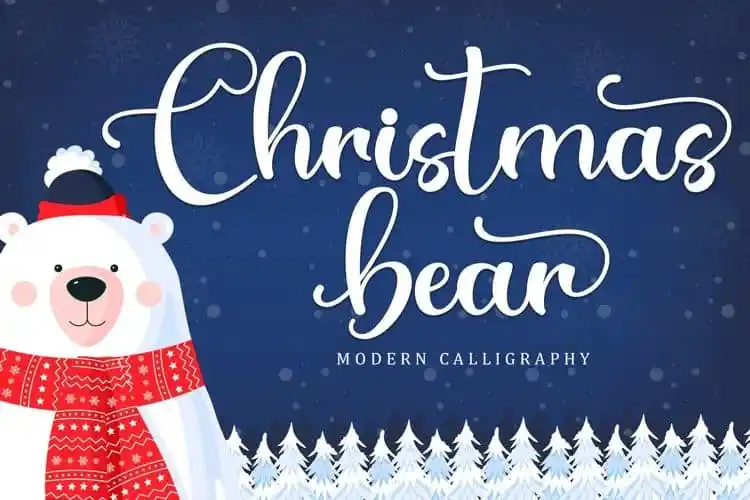
Christmas Bear Calligraphy Font é uma bela tipografia moderna criada por Sakha Design. Esta fonte traz beleza e elegância ao seu texto ou marca, tornando-a mais sofisticada ou atraente. É perfeitamente adequada para um amplo espectro de aplicações, como cartões de visita, convites, adesivos, camisetas e até mesmo peças de fotografia. Além disso, é uma ótima escolha para elementos personalizados em posteres ou retratos, sendo especialmente útil quando você está buscando criar um design único. Seja para fins pessoais ou profissionais, Christmas Bear Calligraphy Font é a fonte perfeita para quem busca uma solução de escrita elegante e única.